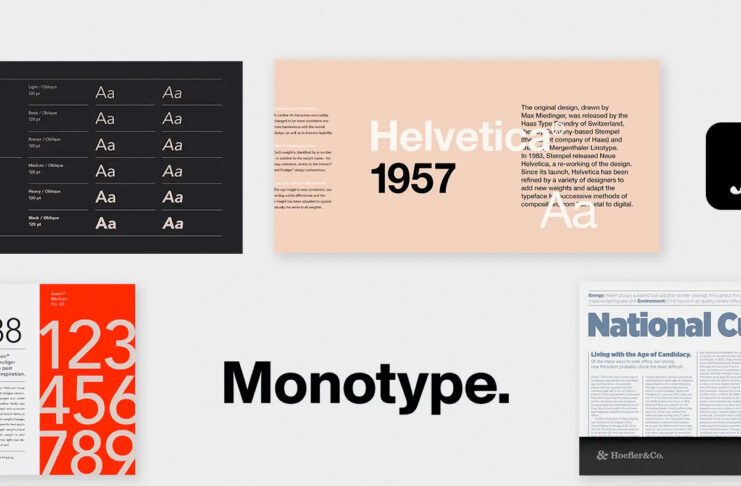
Adobe, 1500 nuovi font con la Creative Cloud
Adobe ha deciso di aggiungere 1500 font ad Adobe Font, la libreria di caratteri offerta agli utenti della Creative Cloud, caratteri utilizzabili con applicazioni quali Photoshop, Illustrator, InDesign e alti software ancora, che ora includono anche molti dei font più noti di Monotype.
La software house di San Jose (California) fa sapere che più di 750 nuovi font sono offerti in collaborazione con Monotype Imaging, titolare di licenze su font quali Helvetica, Gotham e Avenir. L’update della libreria include versioni aggiornate di Times New Roman (tra i più noti caratteri tipografici con grazie), Arial (font senza grazie presente in Windows, macOS e di serie con molte stampanti PostScript)  e Proxima Nova (un sans-serif che ora supporta ancora più lingue).
Tornando ai font aggiornati, Adobe riferisce del supporto a lingue quali: arabo, cinese, giapponese, coreano, thai, hindi e altre ancora.